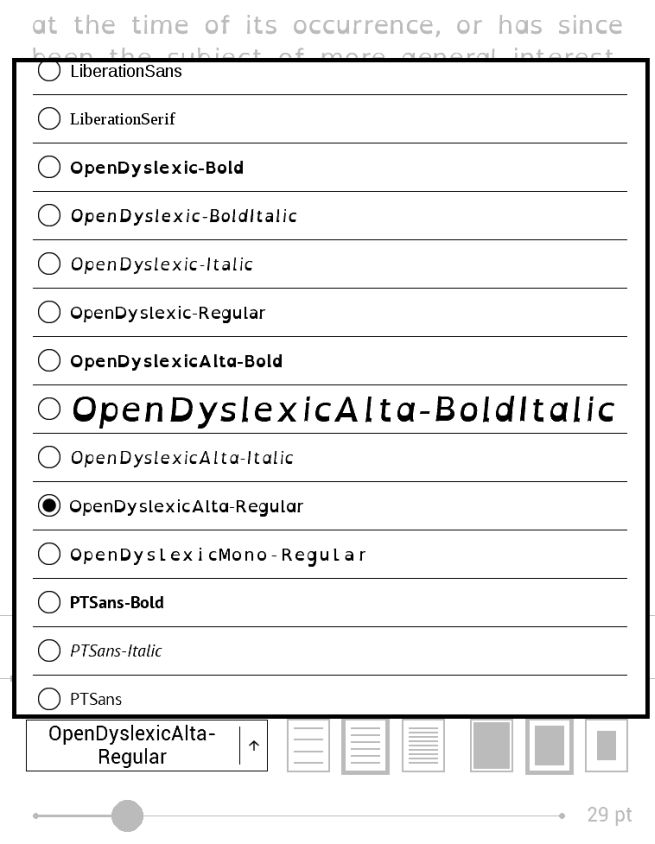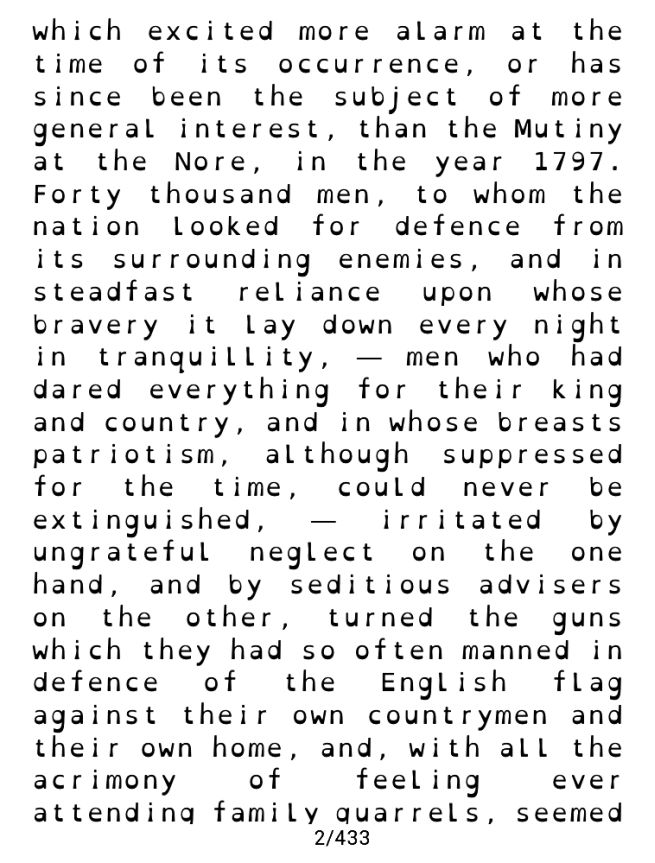
OpenDyslexic - nowa czcionka dla dyslektyków w czytnikach PocketBook
PocketBook wprowadził nowe oprogramowanie dla swoich czytników zawierające czcionkę OpenDyslexic, mającą ułatwiać dyslektykom czytanie tekstów na czytnikach tej firmy.
Czcionka OpenDyslexic, dostępna w oprogramowaniu 5.9 dla modeli PocketBook Touch Lux 3 oraz PocketBook Touch Lux 2, ma pomagać osobom, które zmagają się z różnymi formami dysleksji.
Specjalnie opracowany krój liter ma ułatwiać rozpoznanie najczęściej mylonych znaków. W zestawie celowo pogrubiono "ogonki", wielkie litery i znaki interpunkcyjne oraz zastosowano delikatne nachylenie wybranych samogłosek i spółgłosek.